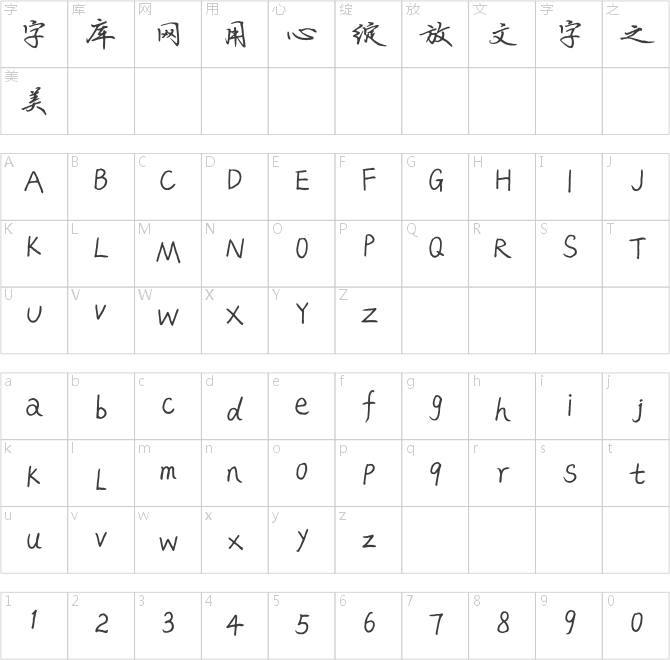
云峰寒蟬體 詳情頁
字體名稱: 云峰寒蟬體
云峰寒蟬體
云峰寒蟬體,一款可應用于多場景的手寫字庫,字體大方美觀,筆鋒力道,云峰字庫專注于字庫開發設計,字庫交流QQ群:205961668
云峰寒蟬體字體字庫是一款讓人賞心悅目、百看不厭的中文字體,適合各類廣告和產品包裝設計應用,字體大小4.37MB,格式為ttf字體,上傳用戶是夢逍遙,作者/版權方為云峰字庫